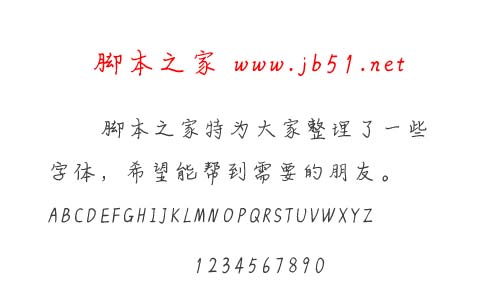
沉魅體字體是一款用于漫畫(huà)設(shè)計(jì)方面的字體,字形纖細(xì)大方得體,整體效果十分出眾,同時(shí)還可廣泛應(yīng)用于平面設(shè)計(jì)、廣告設(shè)計(jì)、報(bào)紙雜志、正文標(biāo)題等領(lǐng)域,歡迎有需要的朋友前來(lái)下載使用。